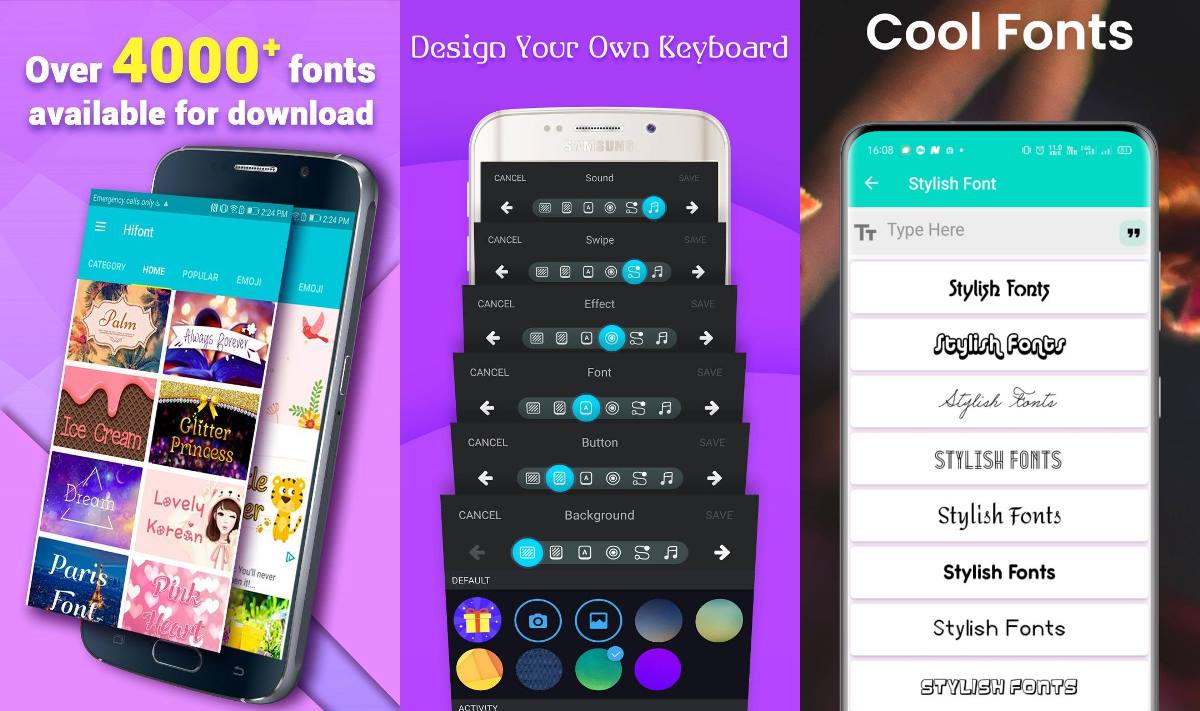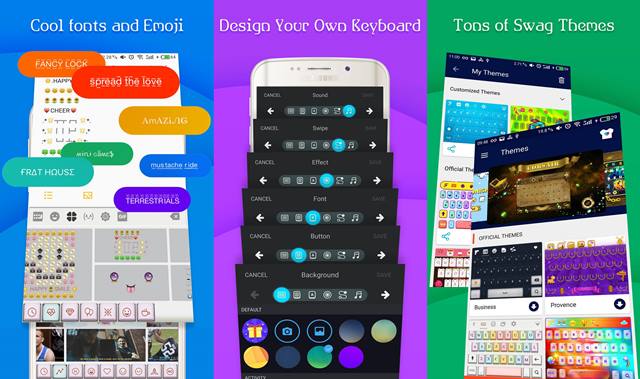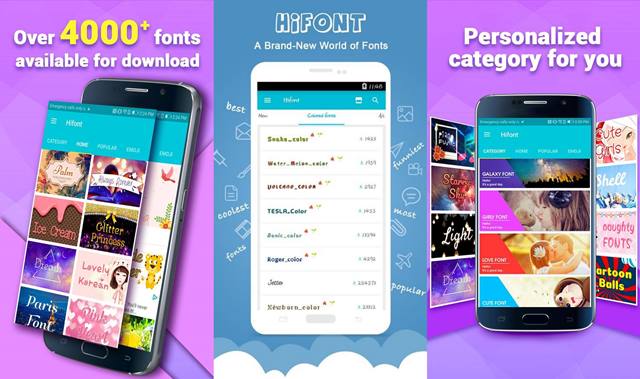
8 Aplikasi Font Aesthetic yang akan Membuat Tampilan HP Lebih Keren
Aplikasi Font Aethetic. (IST)
Aplikasi font aesthetic merupakan salah satu fitur penting bagi android, dengan menggunakan font tampilan Android kamu bisa menjadi lebih menarik
Terlebih HP android hanya menyediakan jenis font yang itu-itu saja, yang akan membuat pengguna nya bosan. Untuk itu layanan google play menyediakan aplikasi font untuk android agar memudahkan kamu jika ingin mengubah font pada Android kamu.
Nah, untuk itu kami akan merekomendasikan beberapa aplikasi font aesthetic terbaik yang dapat kamu gunakan.
Rekomendasi Aplikasi Font Aesthetic Terbaru
Aplikasi Font berikut bisa kamu gunakan untuk mengubah font handphone atau kamu dapat menggunakannya untuk posting pada media sosial.
Hifont
Hifont. (IST)
Aplikasi pertama adalah Hifont. Hifont memiliki segudang font yang sangat lengkap. Semua model unik,pink,romantic,tulisan tangan tersedia dalam aplikasi ini.
FancyKey Keyboard – Aplikasi Font Aesthetic
FancyKey Keyboard - Apk Font Aethetic
FancyKey Keyboard – Apk Font Aethetic. (IST)
Aplikasi ini hanya akan mengubah font pada keyboard yang ada pada HP-mu saja. Keyboard akan membuatmu bisa melakukan custom sesuai dengan seleramu.
Ada beberapa custom yang bisa kamu ubah diantaranya bentuk, background latar, filter dan tentu saja font keyboard-nya. Selain aplikasi ini, masih ada banyak aplikasi keyboard terbaik yang dapat kamu gunakan.
iFont
iFont. (IST)
Pada aplikasi font aesthetic selanjutnya ada iFont, aplikasi ini memiliki banyak sekali jenis font. Terlebih pihak developer nya sering melakukan update font-font terbaru.
Tidak hanya itu, iFont juga bisa mengubah warna dan ukuran font yang akan kamu gunakan. Aplikasi ini juga menyediakan sistem backup untuk jaga-jaga apabila terjadi sesuatu pada aplikasi ini.
Stylish Fonts – Aplikasi Font Aesthetic
Stylish Fonts - Apk Font Aethetic
Stylish Fonts – Apk Font Aethetic. (IST)
Selanjutnya adalah aplikasi Stylish Fonts, aplikasi ini memiliki style font yang beragam yang tidak akan membuat kamu bosan ketika menggunakannya.
Fontli
Fontli merupakan aplikasi yang bisa membantumu mengubah gaya font pada jenis HP apapun.
Aplikasi ini juga sangat mudah dipahami karena sudah dilengkapi dengan cara penggunaannya. Kamu juga bisa membuat anime lucu dan juga mengeditnya dengan desain teks yang berbeda.
Fontli memiliki fitur terbaik yang bisa membuatmu menemukan pengguna aplikasi ini untuk berbagi foto editan yang mereka posting.
TextSwag, Typography Generator
Aplikasi font aesthetic berikutnya yang bisa kamu gunakan adalah TextSwag. Aplikasi ini dapat mengubah kata-katamu menjadi sebuah desain teks foto yang estetik.
TextSwag juga cocok kamu gunakan untuk membuat gambar model kutipan estetik dengan berbagai pilihan gaya font.
Setelah melakukan pengeditan kamu dapat membagikan hasil karyamu di media sosial. Meskipun mudah digunakan tetapi aplikasi ini memiliki beberapa bug yang cukup serius.
Font Changer
Sesuai dengan namanya, Font Changer merupakan aplikasi yang bisa kamu nikmati secara gratis.
Aplikasi font terbaik ini dapat mengganti font pada setiap kata-kata yang kamu masukan ke dalam aplikasi yang kamu miliki.
Terdapat lebih dari 150 gaya font yang bisa kamu nikmati dari aplikasi ini. Kamu bisa menggunakan font tersebut untuk mengubah kata-kata yang kamu posting di media sosial agar terlihat lebih estetik.
Gothic Fonts for FlipFont Free
Jika kamu menyukai tulisan yang bergaya gothic,kami sarankan untuk menggunakan aplikasi ini.